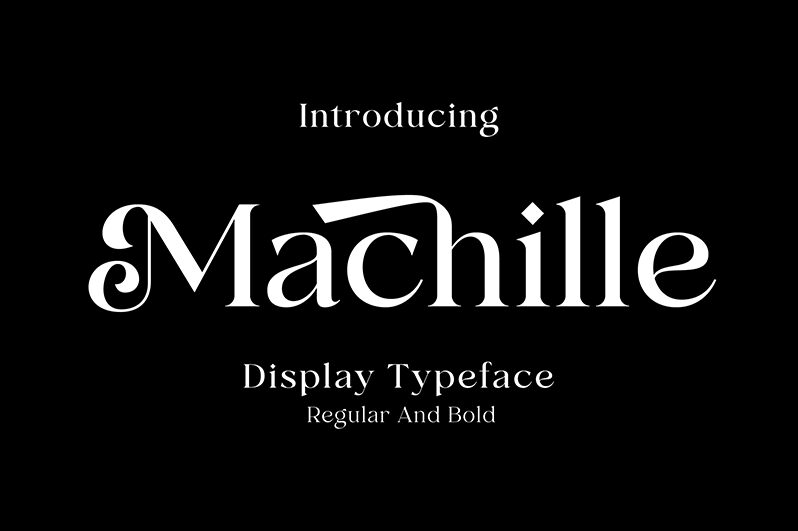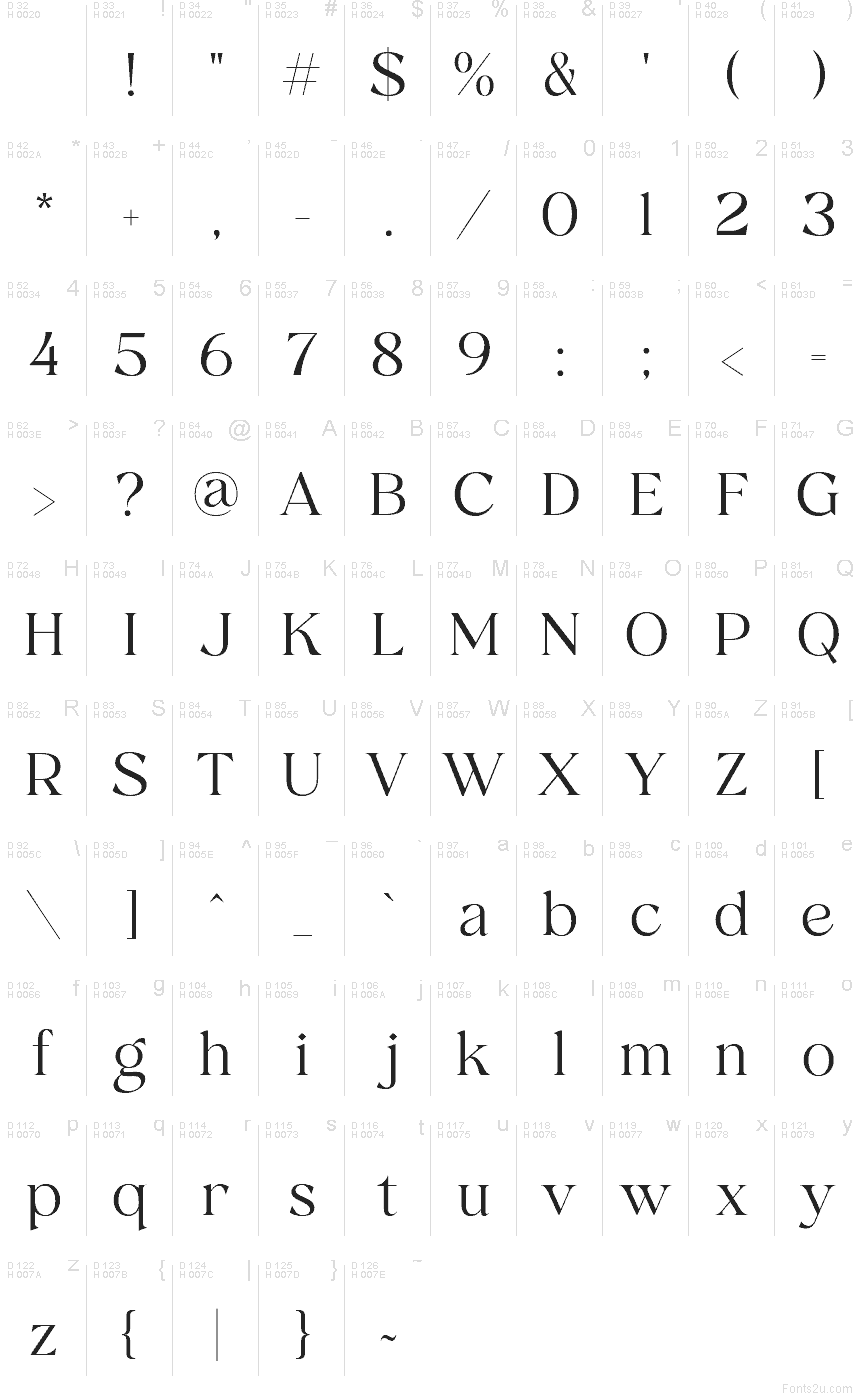
Machille di Akhmad Reza Fauzi è un carattere con grazie gratuito e ad alto contrasto, caratterizzato da proporzioni slanciate ed eleganti. Le sue grazie filiformi e le curve ampie e piene trasmettono una sensazione nitida e teatrale.
Il branding per la moda è il suo contesto ideale, soprattutto per confezioni di profumi e copertine di riviste che valorizzano i netti contrasti tra tratti sottili e spessi. La forma delle lettere può inoltre definire una raffinata identità di prodotto per marchi di cosmetici e gioielli, dove le linee allungate conferiscono un'aria editoriale.